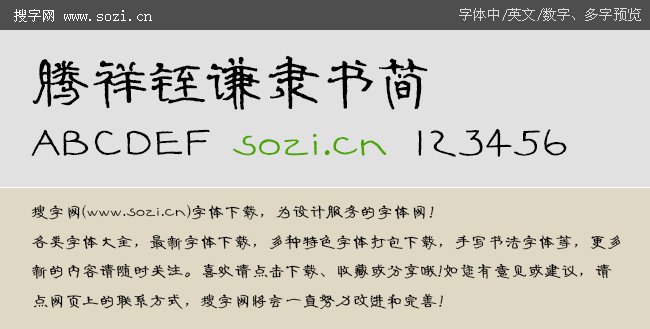
騰祥铚謙隸書簡
搜字網(wǎng)提供一款騰祥铚謙隸書簡中文藝術(shù)字體下載,騰祥铚謙隸書繁字體是一款手寫風(fēng)格的隸書字體,字體樸素?zé)o華,飽含古時(shí)之風(fēng)韻。 可用于出版印刷、廣告設(shè)計(jì) 網(wǎng)頁設(shè)計(jì)、包裝設(shè)計(jì)、屏幕顯示等領(lǐng)域。